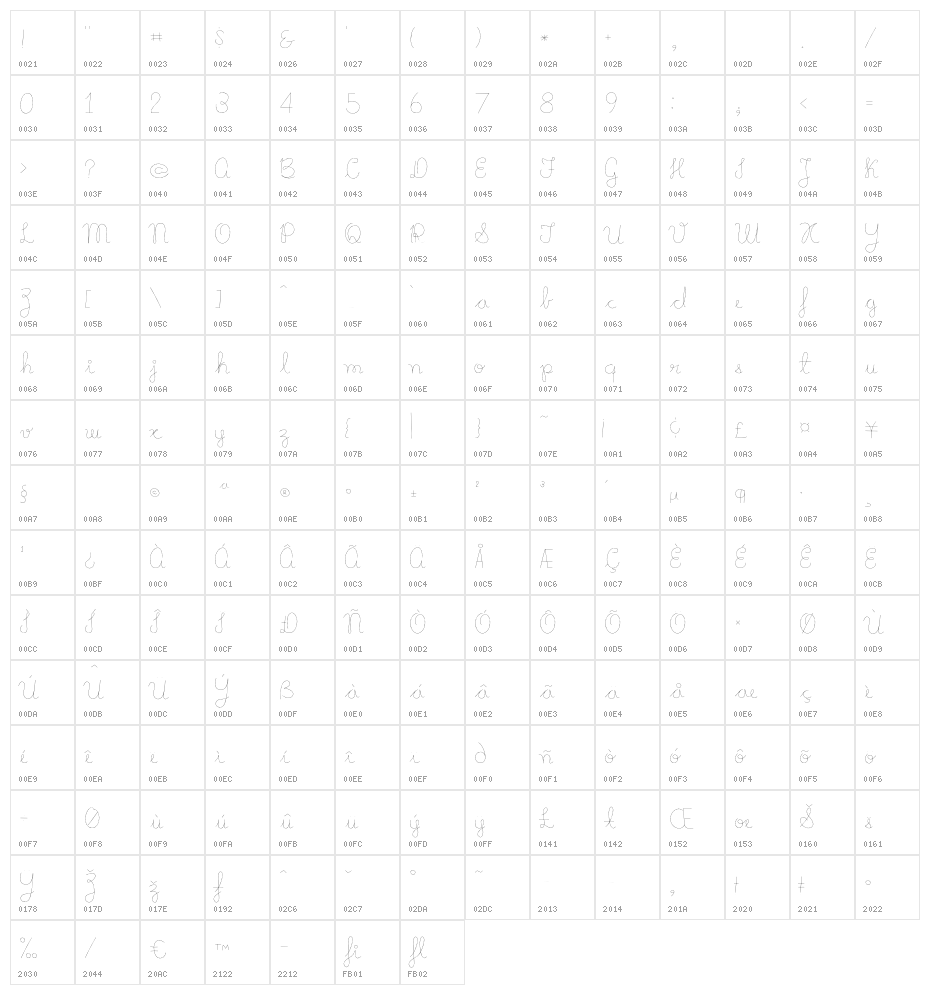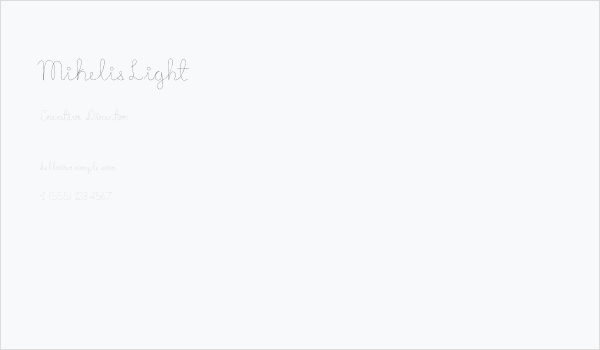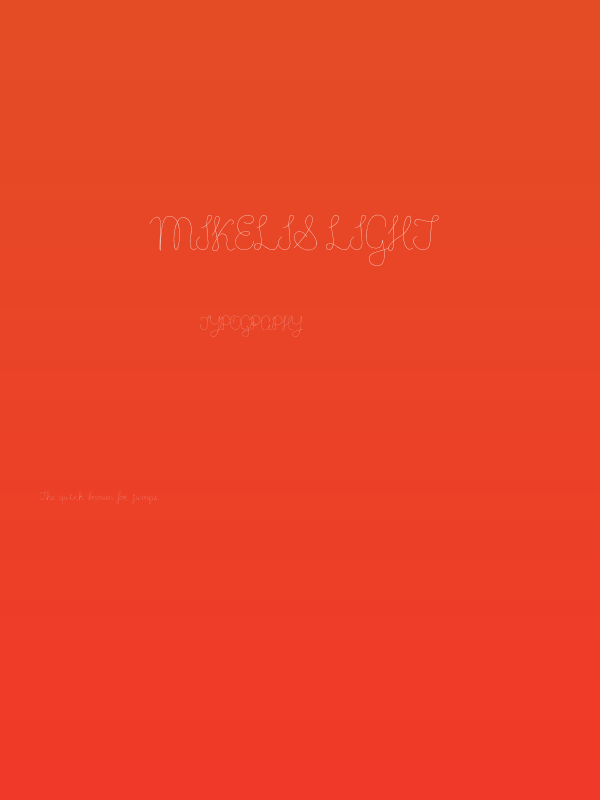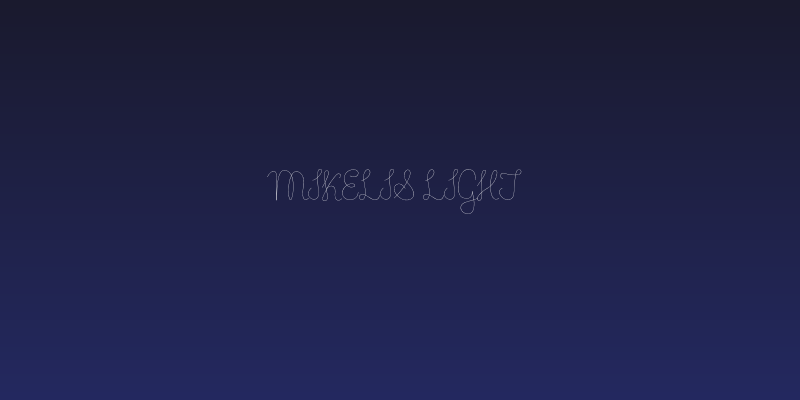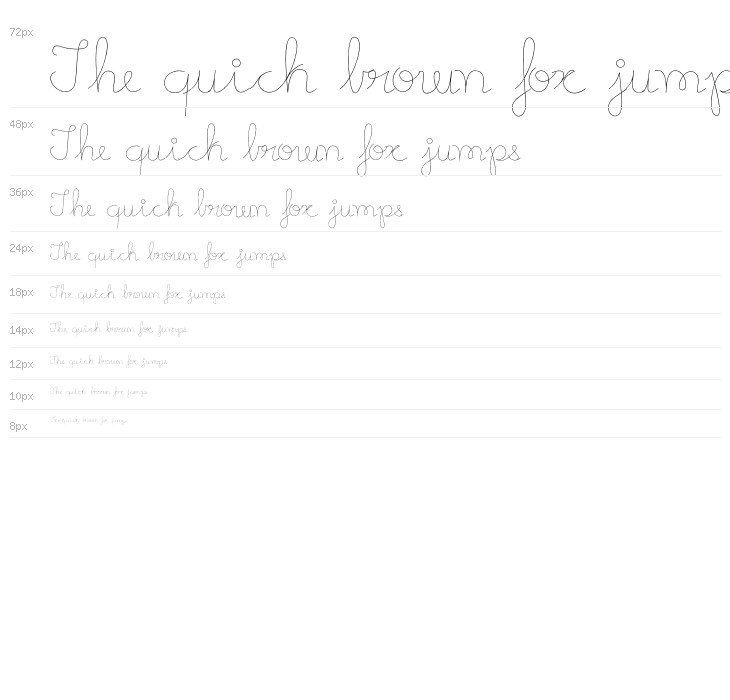
Mikelis-Light Font
| Stile generale | Elegant |
| Caso d'uso | Logos, Invitations, Artistic projects |
| Progetti proposti | Ideal for wedding invitations, elegant branding, personal stationery, and artistic projects requiring a touch of sophistication. |